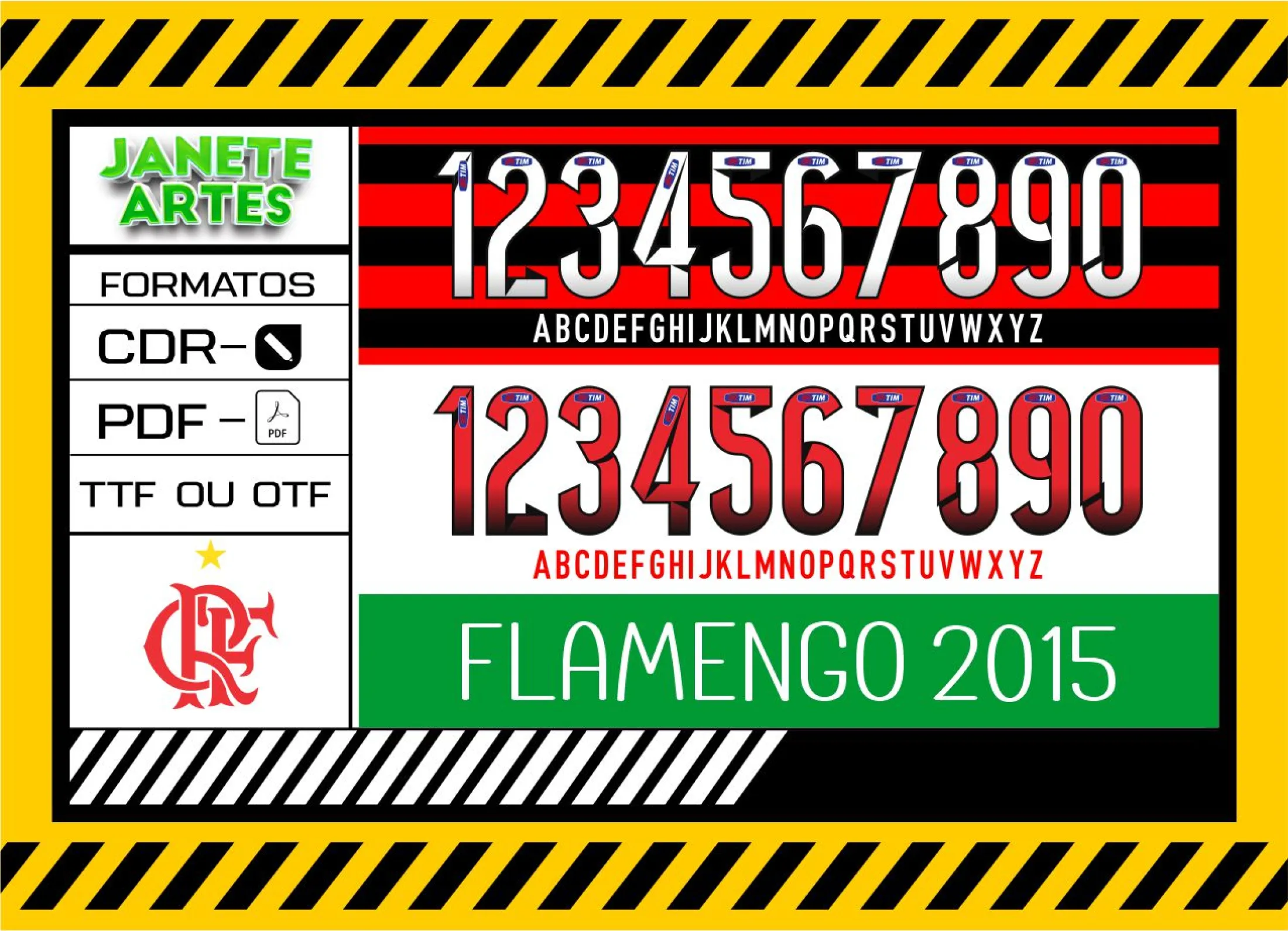
Fonte de Time Tipografia Flamengo 2015
Transforme suas camisetas com a Fonte de Time Tipografia Flamengo 2015. Ideal para personalizar roupas, é um arquivo digital exclusivo para fãs que querem destacar a paixão pelo Flamengo com estilo único.
A Paixão pelo Flamengo em Cada Letra
Imagine a emoção de um torcedor que deseja mostrar seu amor pelo Flamengo de forma única e personalizada. Foi assim que surgiu a ideia de criar a Arte Fonte de Time Tipografia Flamengo 2015. Um arquivo que resgata a identidade visual do time naquele ano marcante, perfeito para estampar camisetas que vão fazer a diferença em jogos, encontros e até presentes para amigos apaixonados pelo rubro-negro. A fonte traz a força e tradição do clube em cada detalhe, fazendo qualquer camisa se transformar numa peça exclusiva e cheia de história.
• Personalize facilmente suas camisetas para uso próprio, eventos, times amadores ou presentes.
• Você poderá adaptar tamanhos, cores e posições da fonte para criar o design perfeito.
• Ideal para camisetas de algodão ou poliéster, com fundo preferencialmente preto ou branco para maior destaque.
• Combine com outras cores nas letras para dar mais vida ao design.
• Perfeito para festas, reuniões de torcida, eventos esportivos e presentes especiais.
• Guarde como opção para criar uniformes ou brindes que simbolizem a união do seu grupo.
• Posso usar em qualquer tipo de camiseta? Sim, mas cores claras ou escuras valorizam bastante o design.
Com a Arte Fonte de Time Tipografia Flamengo 2015 você cria camisetas que expressam sua paixão pelo Flamengo em grande estilo. Aproveite e personalize fácil, rápido e com qualidade profissional! ⚽🔥